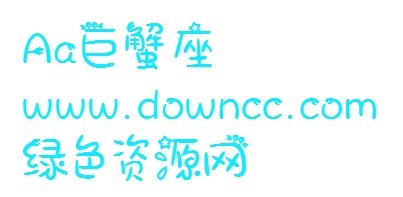
巨蟹座字體有兩個(gè)版本,一款是有著可愛螃蟹外觀的字體管家巨蟹座常規(guī)字體,一款是有著特色裝飾的aa巨蟹座常規(guī)字體,各有特色,歡迎大家下載,選擇你喜歡的藝術(shù)字體使用!
這款美化字添加了小螃蟹的元素,顯得格外的活潑。外表冰冷,但內(nèi)心善良,和熟悉的人他會(huì)很熱情,他會(huì)很盡力的讓他身邊的人感受到做他的朋友和不做他的朋友有明顯的區(qū)別。 這就是巨蟹的人格魅力。
aa巨蟹座和字體管家巨蟹座均是采用同樣的字體模板,一個(gè)讓字體鑲嵌在張牙舞爪的螃蟹圖案中,一個(gè)只是將部分筆畫進(jìn)行修飾更顯小巧,綠色資源網(wǎng)小編為大家?guī)韮煽钭煮w的下載,歡迎體驗(yàn)哦!